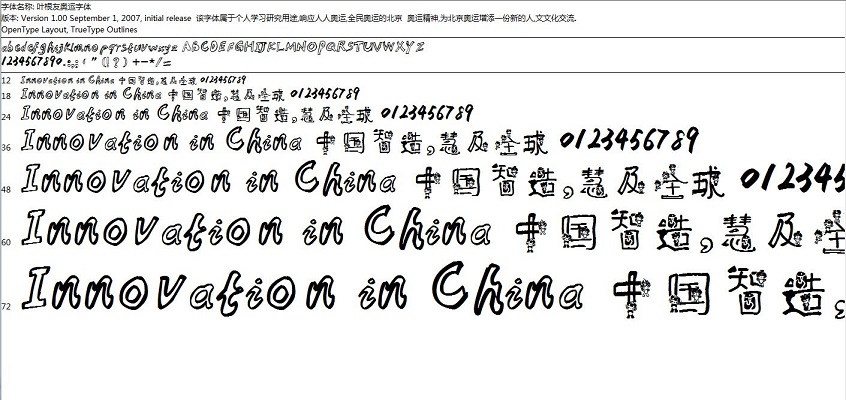
葉根友奧運(yùn)字體是由葉根友先生特地為08北京奧運(yùn)準(zhǔn)備的一套書法字體,該字體結(jié)合了大量奧運(yùn)特色創(chuàng)作而出,十分有象征意義,感興趣的朋友們快來下載吧!
在2007年8月8日距離奧運(yùn)會(huì)倒計(jì)時(shí)一年之際,由著名書法家、連筆空心字吉尼斯紀(jì)錄保持者、五筆同書世界首創(chuàng)者葉根友先生親自書寫創(chuàng)作,中華簽名網(wǎng)和書體坊聯(lián)合開發(fā)的一套字體-《葉根友奧運(yùn)字體紀(jì)念版》即每個(gè)中文漢字都有 “中國印·舞動(dòng)的北京”或者“奧運(yùn)五福娃-北京歡迎您”。其根據(jù)中國漢字的特點(diǎn)進(jìn)行創(chuàng)作,如:點(diǎn),就用“中國印·舞動(dòng)的北京”來代替;底橫劃或者長橫以及豎劃和四點(diǎn)水就用奧運(yùn)五福娃來代替。該款字體屬gb2312字體庫,共6763個(gè)漢字的標(biāo)準(zhǔn)字庫。